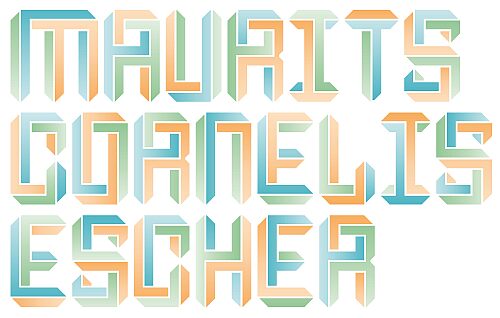
Escheresk, bezpłatny krój typu display autorstwa Tobiasa Sommera, przenosi futurystyczne liternictwo w świat ostrej geometrii i przestrzennych iluzji w stylu Eschera. Wielkie litery zbudowane są z poskładanych, przeplatających się linii, a twarde krawędzie i przesunięcia płaszczyzn sprawiają, że znaki nabierają architektonicznego charakteru.
Ten font świetnie sprawdzi się na okładkach albumów elektronicznych, eksperymentalnych plakatach, ekranach startowych gier, identyfikacji wizualnej festiwali czy w projektach science-fiction. Szczególnie dobrze wygląda w krótkich nagłówkach i tytułach, gdzie labiryntowa konstrukcja ma przestrzeń, by w pełni wybrzmieć, a powtarzające się ostre cięcia tworzą zwartą całość.